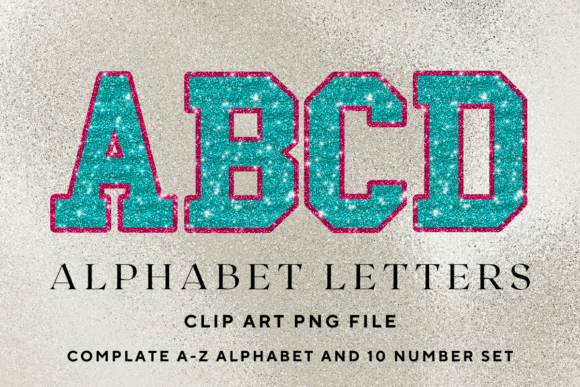
Glitter Alphabet Varsity Sport Letters
Việc tìm kiếm các thành phần thiết kế phù hợp có thể là một thách thức, nhưng Glitter Alphabet Varsity Sport Letters cung cấp một bộ sưu tập đặc biệt giúp nâng tầm công việc của bạn ngay lập tức.
Được chế tác với độ chính xác cao, Glitter Alphabet Varsity Sport Letters cung cấp các vector sạch, kiểu chữ mượt mà và giấy phép thương mại để bạn yên tâm.